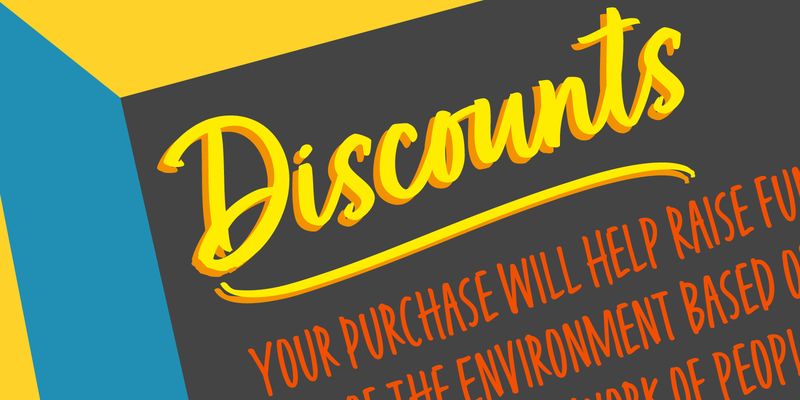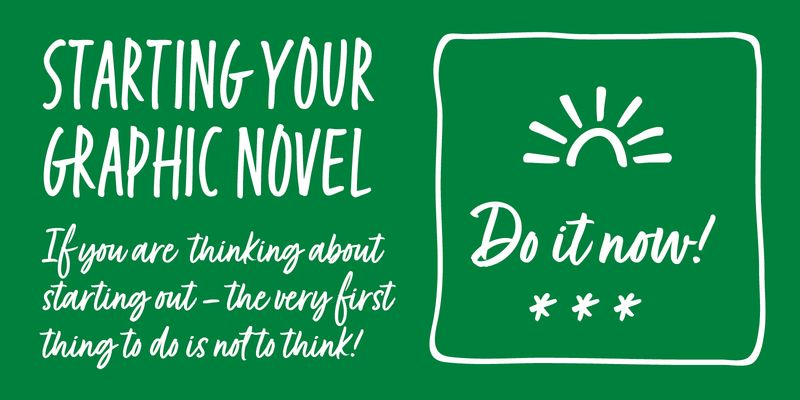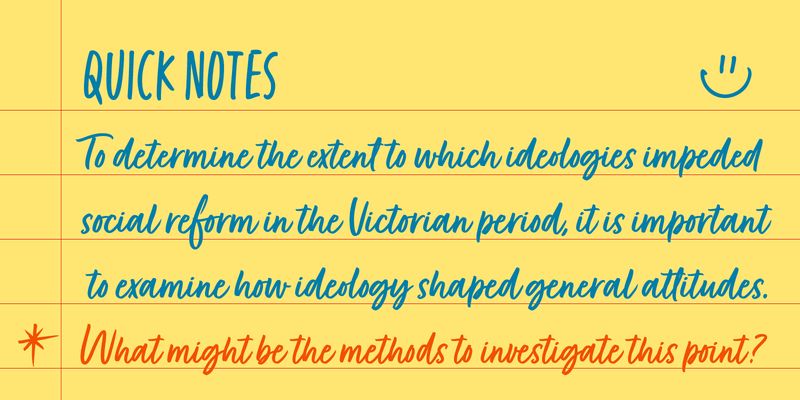
Aerotype è stata fondata nel 1995 per ospitare una piccola collezione di caratteri tipografici creata da Stephen Miggas. Oggi Aerotype è conosciuta soprattutto per i caratteri scritti a mano quali Fave, Turbinado e Zooja, digitalizzazioni di caratteri in legno quali Thunderhouse con la sua patina originale e altri font per la visualizzazione.